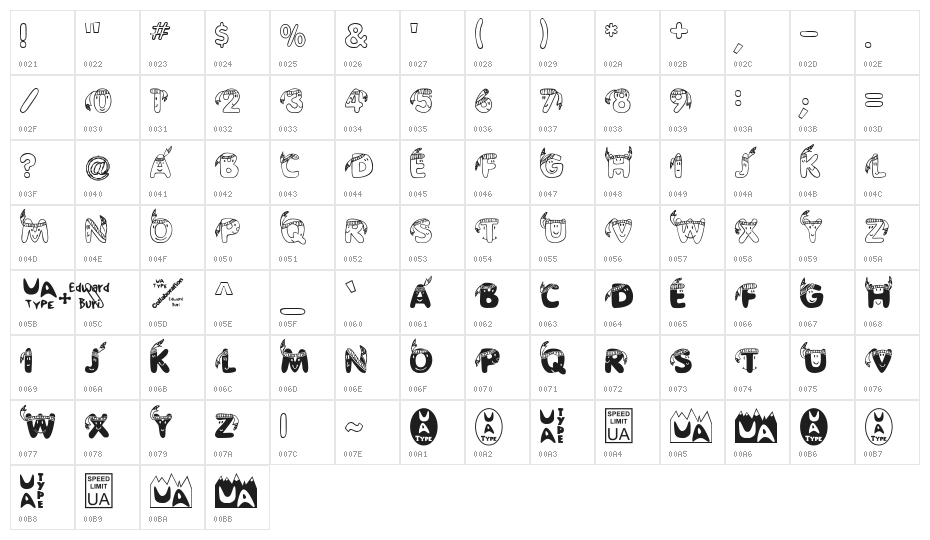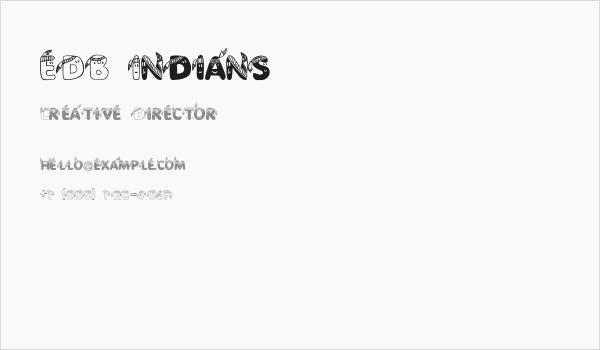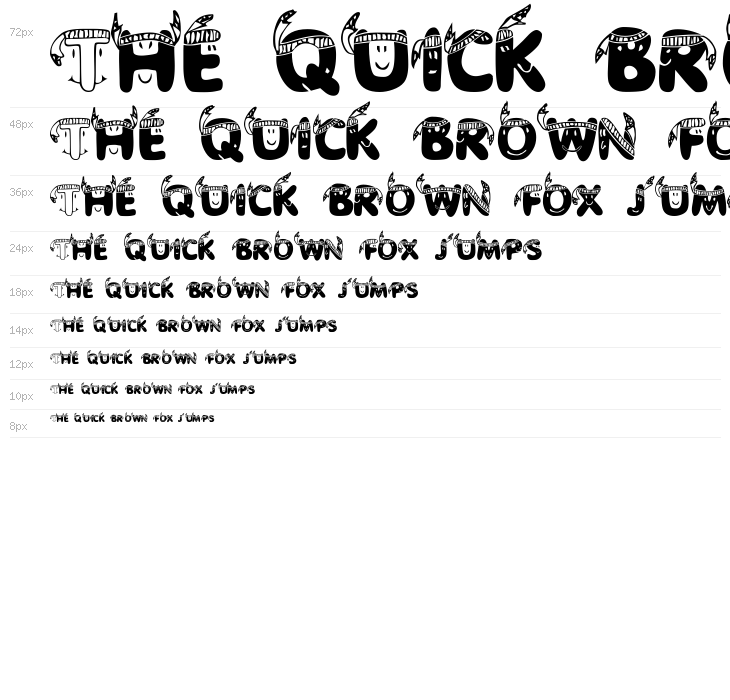
EDB Indians Font
| Progetti proposti | Great for children's books, posters, event invitations, and branding that requires a playful and artistic touch. |